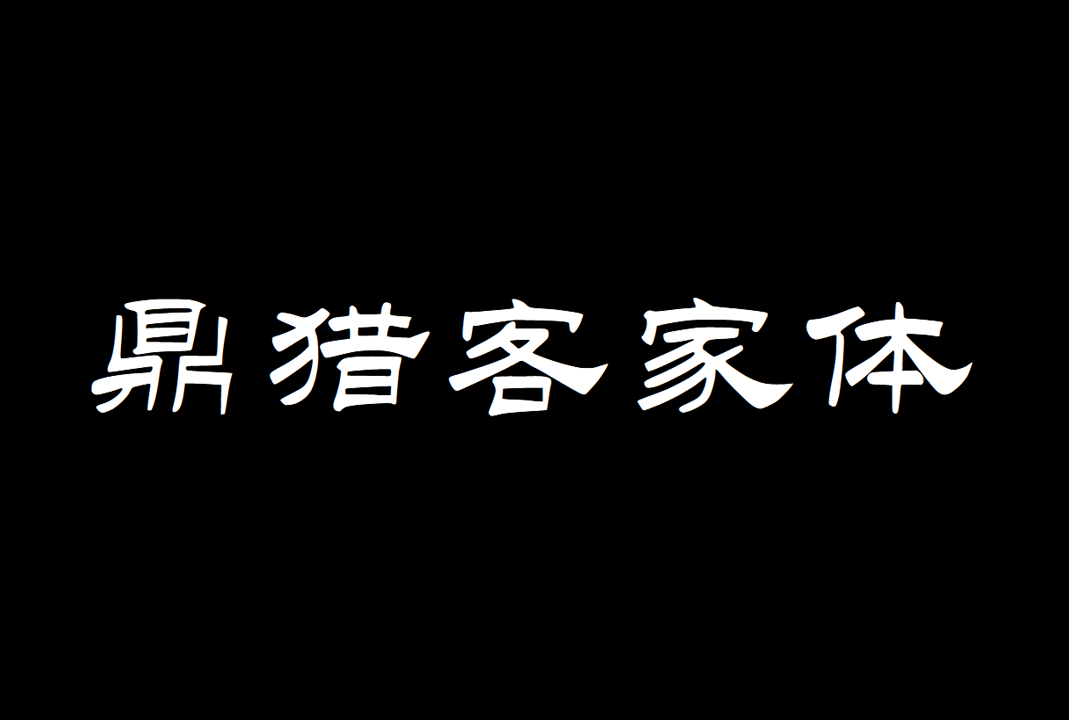
鼎猎客家体(dingliehakkafont)为一款原创字体,是由鼎猎咨询于微信公众号发布声明的一款中文免费商用字库,具有其独特的字形风格,适用于广告、书籍、海报等多个场合,字库特别增加了客家话专属汉字数十个。
鼎猎客家体(dingliehakkafont)根据简体中文汉字编码国家标准(GB2312编码)设计,包含6789个简体汉字,可覆盖大部分使用场景。